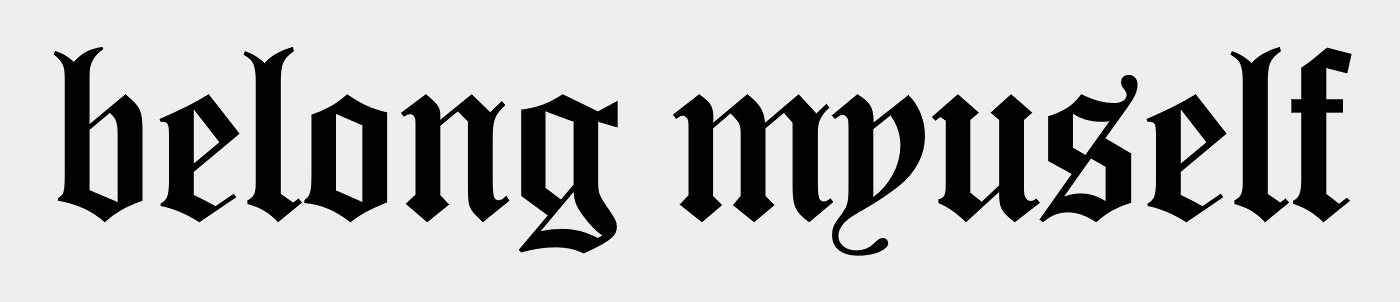
Suche Schrift von diesem Tattoo
Würde mir gerne selbst ein Wort in dieser besonderen Old English Schrift stechen lassen, allerdings konnte ich sie bis jetzt leider nirgends finden. Besonders die unteren Haken vom ‚y‘ und vom ‚g‘ gefallen mir daran sehr gut. Es würde mich sehr freuen, wenn jemand die gleiche oder eine sehr ähnliche Schrift finden könnte. 🙂
Das Bild zeigt den Rücken der Instagramerin ‚phiphibb‘.
Es gibt nur noch wenige Berufe, zu deren Handwerk es gehört, Schriften sauber von Hand zu zeichnen. Dies sind die fast schon ausgestorbenen Schildermaler, Steinmetze, Kalligraphen, die besonders hochwertige Urkunden anfertigen - und eben Tätovierer, und gerade die haben ein besonderes Problem; Ihre zu beschriftendes Material ist nicht flach, sondern mit vielen Rundungen vielfältig gewölbt, und heran muss sich die Beschriftung eben so anpassen, dass diese Beschriftung lebenslänglich gut aussieht. Daher ist die Mehrheit von Beschriftungen menschlicher Körper individuell dafür frei gezeichnet worden, so mit größter Wahrscheinlichkeit auch hier. Es wird also exakt diese Schrift als Computerschrift nicht geben. Möglich, dass man ähnliches in Anleitungsbüchern  für werdende Kalligraphen und Schildermaler findet.
Daher ist die Mehrheit von Beschriftungen menschlicher Körper individuell dafür frei gezeichnet worden, so mit größter Wahrscheinlichkeit auch hier.
Es ist zwar eine erstaunliche und begrüßenswerte Entwicklung* in der Szene zu sehen, aber das Gros der Tätowierer hat nicht unbedingt wirklich Ahnung oder Übung in Schrift. Da wird rumgebastelt und abgeguckt und natürlich auch zu Satzschriften gegriffen. Und wenn man keinen Piker findet, der nicht ausdrücklich auf Schriften spezialisiert ist, ist eine Satzschrift immer die bessere Wahl als gewollt aber nicht gekonnt.
Man findet Old English mit den Unterlängen, aber die haben dann nicht die zwei Spitzen in der Oberlängen.
Andersrum sollte jedem, der etwas zeichnen kann zuzutrauen sein den Schwung beim g etwas abzuwandeln und das y aus u und dem Schwung zusammenzubauen ...